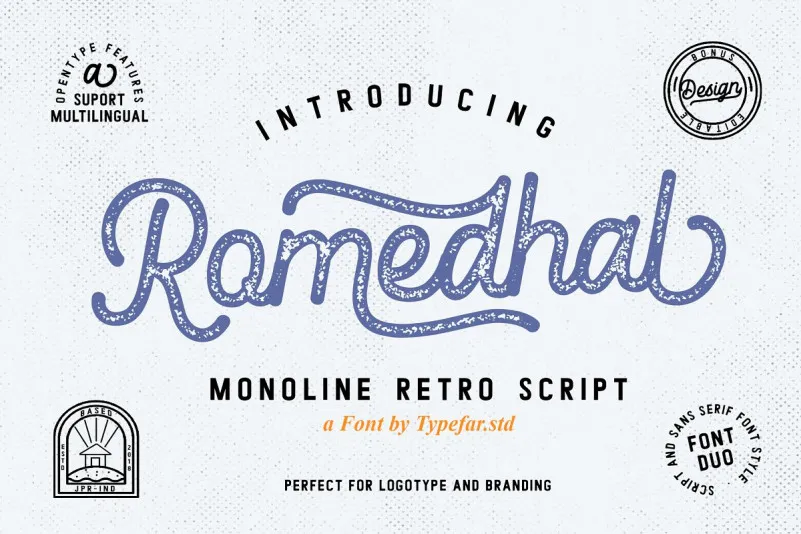
Romedhal Script Font – Download Grátis
Esta nova fonte script vintage, Romedhal Font, traz aos dias nostálgicos com seu toque clássico. Introduzida pela equipe do designer 0001themes, Romedhal é uma mistura de sans-serif e monoline para um estilo retro que se destaca. Suas linhas finas e elegantes são perfeitas para estilos de marca ou logomarcas, com a adição de uma design bonus em formato PSD. Esta versão flexível permite ajustes sutis no editor, tornando-a ideal para aplicação em camisetas, materiais promocionais ou até mesmo um logotipo empresarial. Com Romedhal Font, você pode capturar o espírito dos anos 70 e 80 através de uma fonte moderna e atemporal.